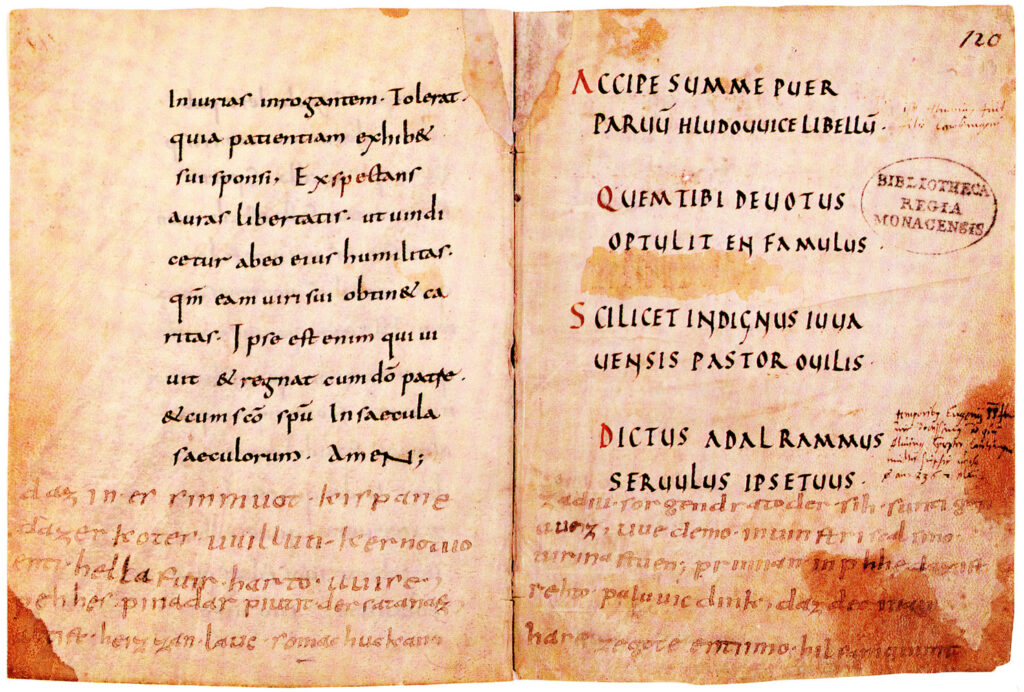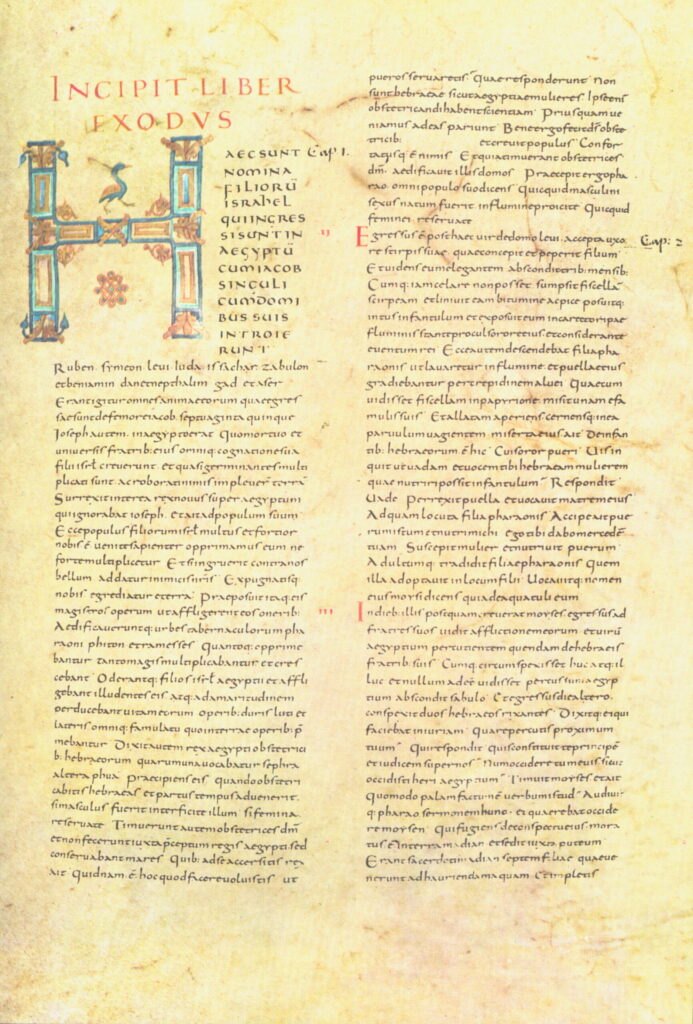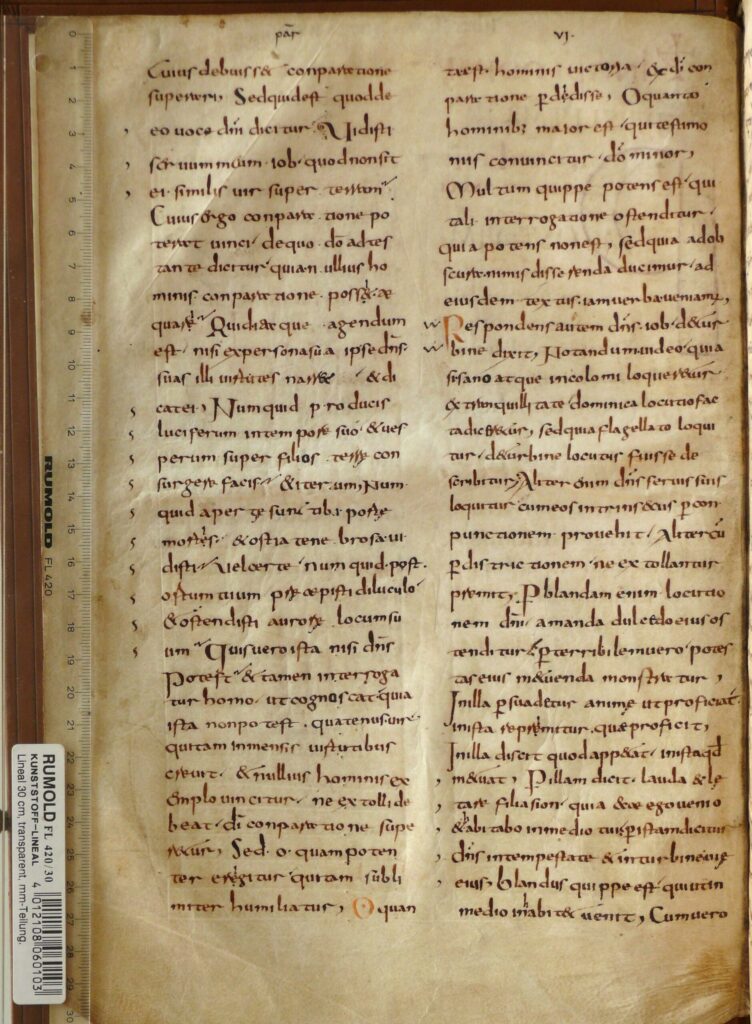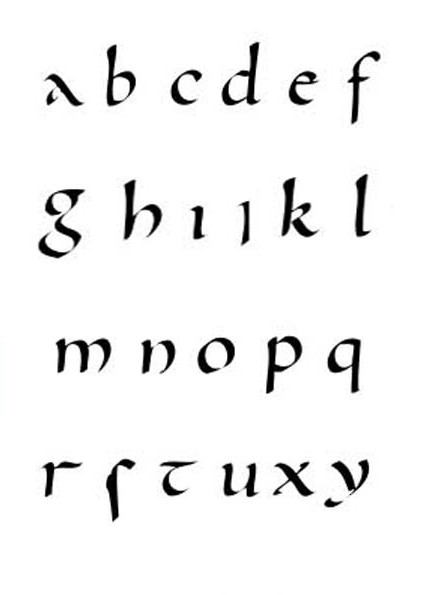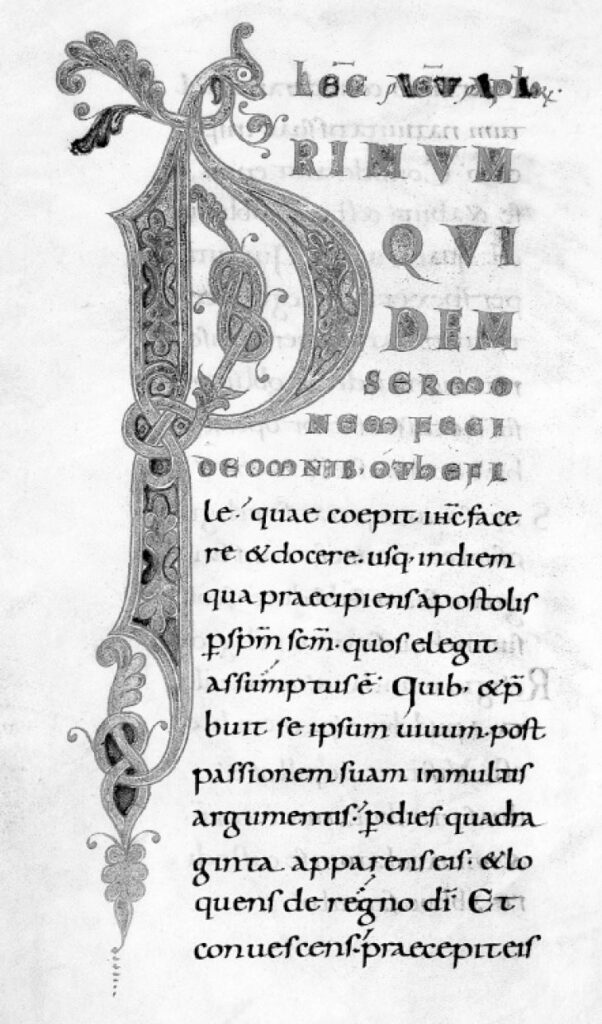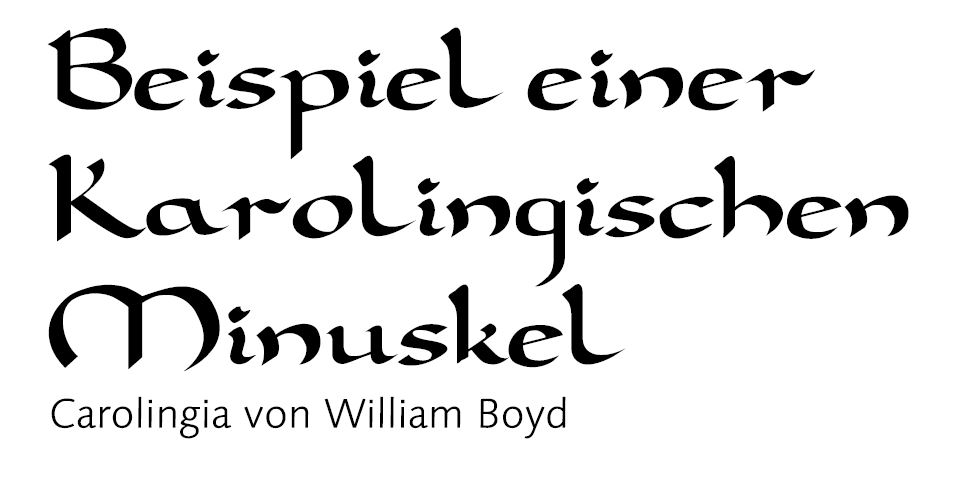
8.–11. Jh.
800 und die Karolingische Minuskel
Unter Karl dem Großen entsteht um 800 die Karolingische Minuskel, eine gut lesbare Rundbogenschrift mit ausgewogenem Schriftduktus auf hohem typografischem Niveau. Erstmals wird eine einheitliche Schrift im gesamten Reich eingeführt, von den Herrschern befohlen und von den Geistlichen umgesetzt. Die Karolingische Minuskel spiegelt damit den politischen Anspruch der Kaiser wider: Schrift wird erstmals gezielt zu politischen Zwecken eingesetzt.
Als Basis dienten die Halbunziale und die römische Kursive. Versalien gab es zunächst nicht; bei Bedarf wurden sie aus der Quadrata, Rustica oder Unziale übernommen. Die Karolingische Minuskel bildet die Grundlage für die Humanistische Antiqua der Renaissance.
1000 und die Romanik
Um 1000 wandelt sich der Stil der Karolingischen Minuskel zur Romanik. Der romanische Kunststil erreicht im 12. Jahrhundert seine Blüte, sichtbar noch heute an zahlreichen Kirchenbauten in Europa. Charakteristisch sind wuchtige Türme, Rundbögen und ornamental verzierte Fassaden – berühmte Beispiele sind die Dome zu Speyer, Worms und Mainz. Die Bauwerke werden höher, die Schrift steiler. Auch die Karolingische Minuskel passt sich dieser Stiländerung an und entwickelt sich weiter bis hin zur gotischen Form.